Какой шрифт используется Вконтакте для надписей на картинках
Сегодня я слегка озадачился поиском подходящего кириллического шрифта, который бы было можно использовать в фотошопе для нанесения красивого текста на картинки.Уверен, многие знают, что большинство шрифтов, которые установлены на компьютере по умолчанию или те, что были отдельно занесены в коллекцию не поддерживают русские символы (буквы).
В общем, я решил найти какой-нибудь русский шрифт для фотошопа, и почему-то сразу же вспомнил про красивые надписи, которые используются на большинстве картинок в социальной сети «Вконтакте».
Пример шрифта
На этой картинке один из примеров шрифта, который я хотел найти и добавить в свой Photoshop CS6, но вот не задача – найти его оказалось не так уж и просто.
Сначала я решил воспользоваться поисковой системой Яндекс, что бы найти хоть какие-то зацепки, но перебрав все возможные варианты для запросов, я так ничего и не нашёл.
И лишь немного позже, прибегнув к ответам от Mail.ru в одном из комментариев я нашёл что-то похожее. Оказалось для надписей на картинках ВКонтакте чаще всего используют шрифт под названием Lobster (Лобстер).
Lobster — шрифт для надписей на картинках Вконтакте
PS: Пожалуй, это лучший из шрифтов с поддержкой русских букв!
В связи с тем, что на сайте ВКонтакте шрифт достаточно мелкий, у многих людей, которые испытывают проблемы со зрением, быстро устают глаза. Следовательно, возникает потребность уменьшении или увеличении масштаба. В этой статье мы расскажем о всех возможностях для изменения шрифтов, которые доступны в рамках сайта ВК.
Описание шрифтов в ВК
Многие юзеры задаются вопросом, какой шрифт используется в сервисе ВК? В действительности vkontakte использует три вида текста: Tahoma, Arial и Verdana. Непосредственный подбор оптимального шрифта, который будет использоваться на устройстве, выполняет веб-обозреватель. Данная процедура выполняется практически мгновенно. Tahoma используется по умолчанию. Если браузер, через который вы вошли на сайт социальной сети не поддерживает его, он будет выбирать второй вариант – Arial, затем третий – Verdana. Если интернет-обозревателю не удается подключить ни один из этих вариантов, тогда он попытается использовать шрифт из локальных настроек устройства.
Способы изменить шрифт в ВК
Улучшить читабельность текста можно с помощью:
- Настроек сайта.
- Настроек интернет-обозревателя.
- Сторонних средств.
Использование готовых стилей оформления
Увеличение шрифта
Способ №1:
- Зайдите в свою учетную запись VKontakte, затем перейдите в раздел „Настройки“.
- Пролистайте немного вниз, в „Настройках внешнего вида“ поставьте отметку возле „Использовать увеличенные шрифты“. Для уменьшения сделайте наоборот.
Способ №2:
- Перейдите в настройки веб-обозревателя, который используете для входа на сайт.
В разделе „Масштаб страниц“ увеличьте размер текста на странице до того процента, который подходит именно вам.
Отрегулировать масштаб страницы можно с помощью клавиатуры и мышки. Увеличение размера текста – зажмите клавишу „CTRL“ и „+“ или нажмите „CTRL“ и прокрутите колесико мыши вверх.
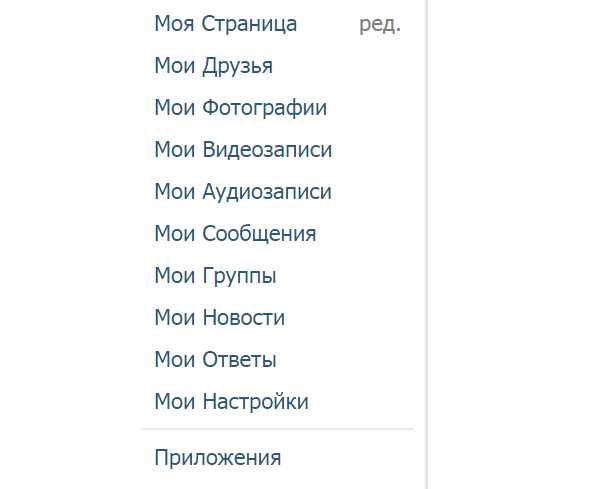
Уменьшение шрифта
На странице профиля зажмите правую или левую кнопку „CTRL“ и прокрутите колесико мыши на себя или нажмите кнопку Ctrl и „-“. Вернуть масштаб страницы на 100% — нажать CTRL и „ноль“ (0).
Жирный шрифт
Социальная сеть предоставляет возможность администраторам при оформлении меню сообществ выделять слова и фразы жирными буквами. Для использования опции понадобится:
- Справа от того места, где набираешь текст, ты увидишь кнопку «Аа» — она и меняет шрифт. При каждом нажатии шрифт меняется на следующий — «Импакт», «Лобстер» и снова «Импакт».